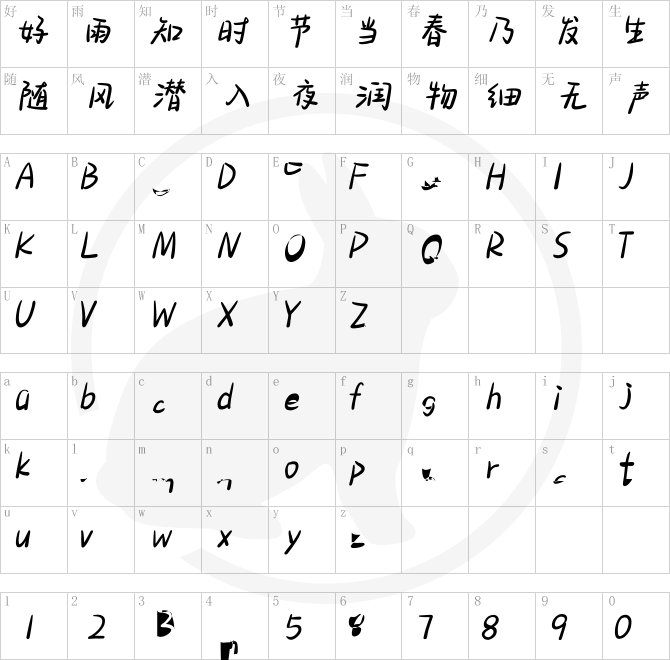
也字工厂蜡笔体
也字工厂蜡笔体,这款字体结构工整、笔画清晰,兼顾美观与易读性,适用于标题、正文、海报、包装、LOGO 等多种场景。字形优雅稳定,风格百搭耐看,适配日常排版与创意设计,让文字呈现更舒适、更具质感。也字工厂蜡笔体一笔一画,皆是细节,以均衡的比例、流畅的线条打造舒适视觉体验,字形端正大气,风格简约现代。无论是商业设计、品牌宣传还是日常排版,都能轻松驾驭,让文字更有格调与力量。也字工厂蜡笔体字体下载。